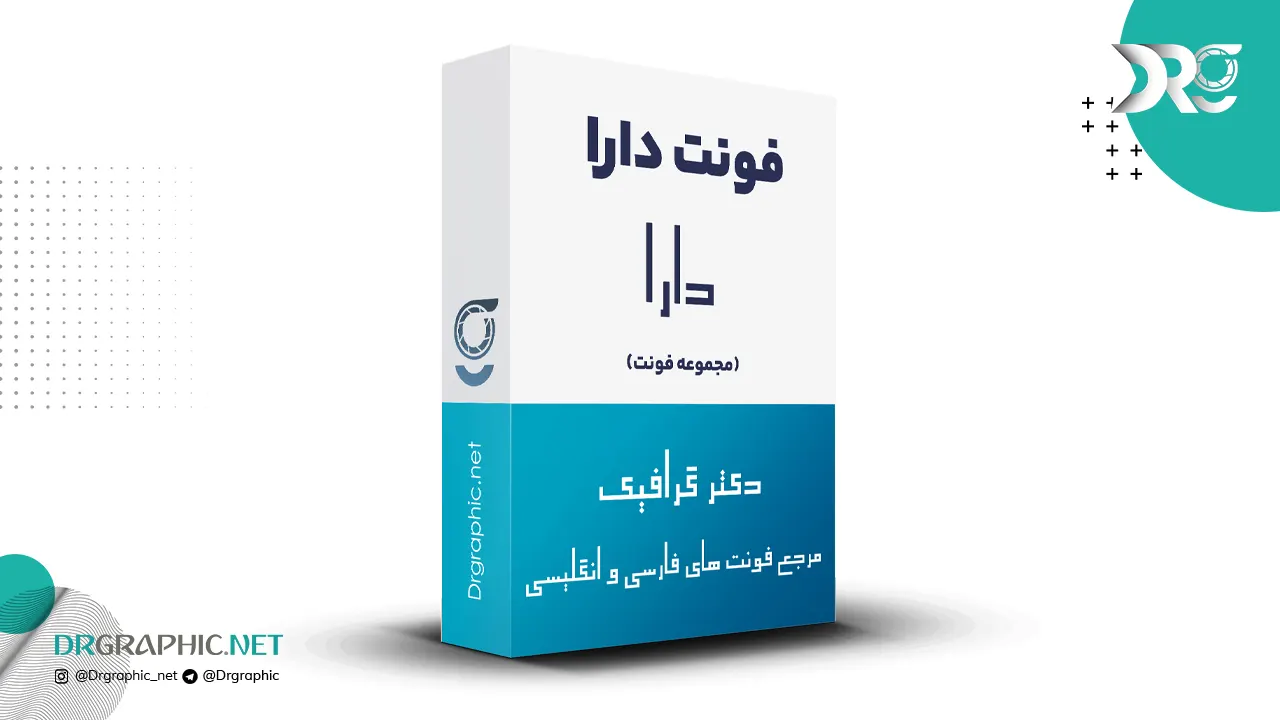
دانلود مجموعه فونت دارا Dara
فونت دارا (dara form) از جمله فونت های می باشد که در طراحی آن از سبک خاصی استفاده شده است که باعث شده این فونت جذاب و پرکاربرد شود که در طراحی گرافیک کاربرد بسیار خوبی دارد. این فونت در وزن regular طراحی و استاندارد سازی شده است. با دکتر گرافیک همراه باشید.
نمونه نوشته با این فونت: